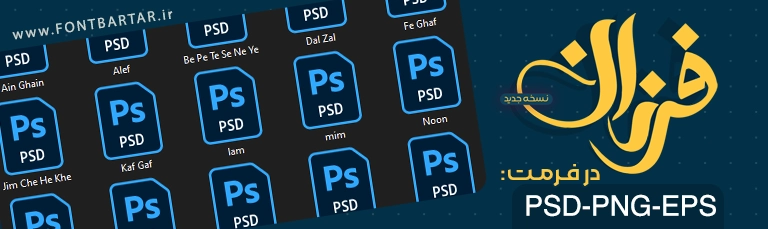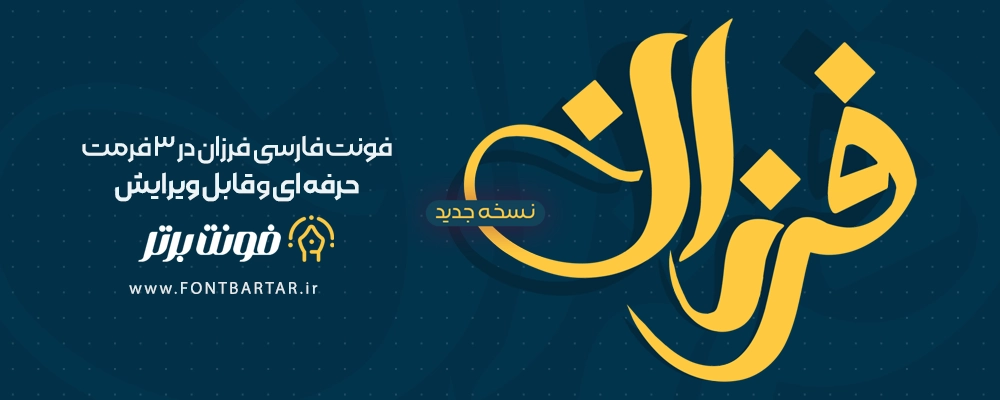
دانلود فونت لوگوتایپ فرزان
فونت فارسی فرزان
Farzan Font
اگر به دنبال یک فونت فارسی خاص، حرفه‌ای و قابل ویرایش برای طراحی‌های لوگوتایپی، تایپوگرافی و پروژه‌های گرافیکی هستید، فونت فرزان دقیقاً همان چیزی‌ست که نیاز دارید. این فونت با طراحی منحصربه‌فرد، ساختار خوش‌خوان و ظاهری زیبا، گزینه‌ای عالی برای استفاده در برندینگ، طراحی لوگو، پوستر، بنر و محتواهای دیجیتال است.
ویژگی‌های فونت لوگو فرزان :
• قابل ویرایش کامل و مناسب برای شخصی‌سازی حرفه‌ای
• طراحی منحصر به فرد با حفظ اصالت خوشنویسی فارسی
• مناسب برای طراحی لوگوتایپ، تیزر تبلیغاتی، بسته‌بندی، چاپ و فضای دیجیتال
• کاملاً سازگار با استانداردهای طراحی مدرن
چرا فونت فرزان را انتخاب کنیم؟
فونت فرزان با بهره‌گیری از فرم‌های نرم، حروف کشیده و ترکیب سنتی و مدرن، حس قدرت و ظرافت را هم‌زمان القا می‌کند. این فونت، نتیجه تجربه و خلاقیت در طراحی فونت فارسی است که برای ساخت لوگو تایپ برند، نام فروشگاه، عناوین مجلات و پروژه‌های گرافیکی سطح بالا بسیار مناسب است.